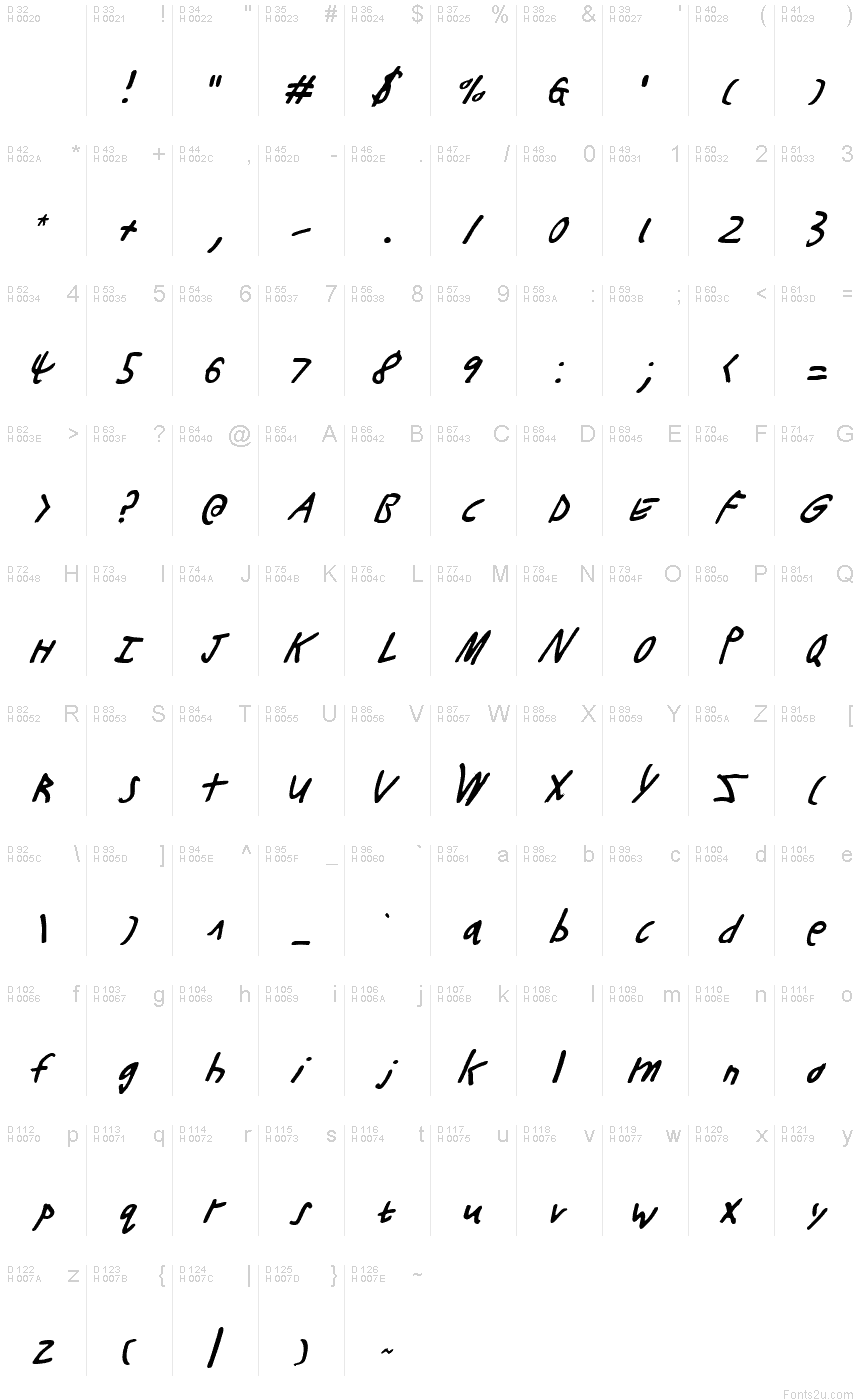
Buttons the Bear Light Italic, od Iconian Fonts, to darmowy krój pisma imitujący pismo odręczne wykonane pędzlem, z zabawnym, nostalgicznym akcentem. Litery pochylają się do przodu dzięki grubym, zaokrąglonym pociągnięciom, a luźne łączenia nadają całości przyjazny, maskotkowy charakter – bliższy malowanym szyldom niż starannej kaligrafii.
Dzięki temu ten darmowy font to naturalny wybór na okładki książek dla dzieci, branding słodyczy, menu kawiarniane, wlepki czy krótkie nagłówki, gdzie jego miękki, wyrazisty rytm gra główną rolę. Świetnie sprawdza się również w tytułach i napisach, ponieważ szerokie kształty pędzla i lekkie pochylenie dodają nawet kilku słowom ciepłego, nieformalnego wyrazu.
Buttons the Bear Light Italic